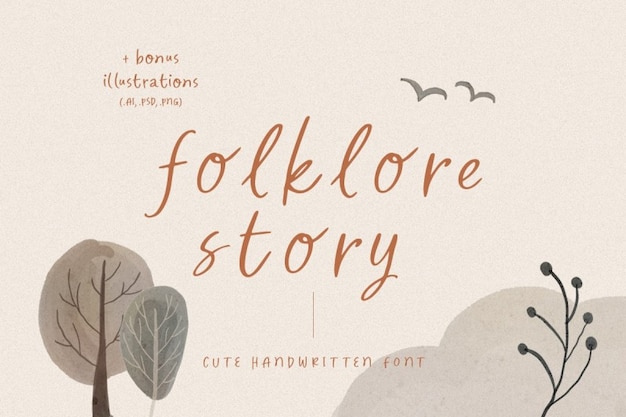
Folklore Story Jenis Huruf
Sarid Ezra
Jenis huruf tulisan tangan yang lucu ini adalah Folklore Story, sebuah jenis huruf yang dibuat oleh Sarid Ezra, yang akan sempurna untuk membuat proyek branding, merchandise, atau sampul buku Anda menjadi berbeda. Hadir dengan versi miring dan tebal serta berisi simbol, huruf besar, huruf kecil, dan dukungan multibahasa. Tunggu apa lagi? Unduh dan pasang sekarang dengan Freepik.